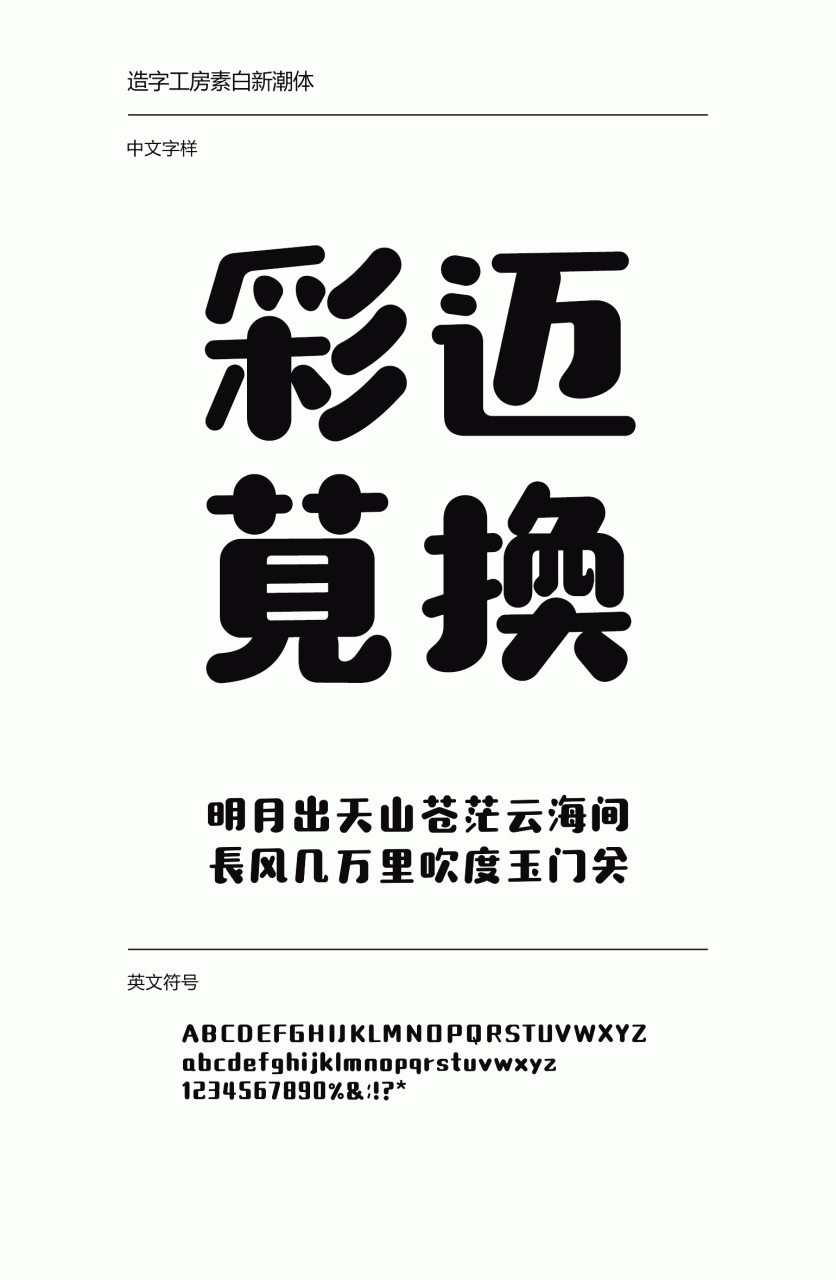
字体简介
造字工房素白新潮体,以浑圆流畅、筋骨俱备为基本设计理念,其字形粗而不重,胖而不臃,风格天真活泼,卡通可爱。此款字体适用于儿童读物、报刊杂志标题、广告设计等视觉环境,本字库在保留其简体字形风格的同时参考旧字形结构、笔画特点,进行了大胆创新及识别性的中和处理,使其有更大的应用空间。本字库采用OpenType/CID格式,Adobe-GB1-5编码。基于中华人民共和国GB2312-80字符集标准,另按需添加101个汉字。共收容字数6864CJK汉字,ASCII常用字符100个。